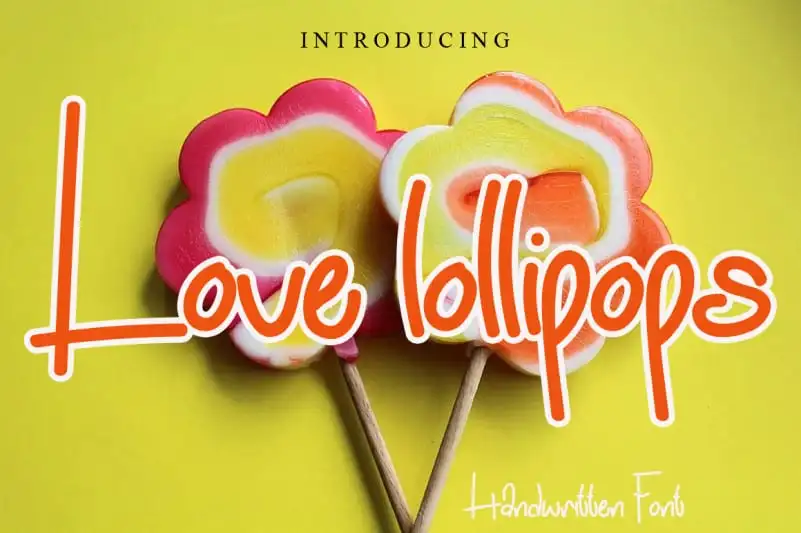
Love Lollipops Font – Fonte Grátis
Love Lollipops Font
A “Love Lollipops Font” é uma elegante escolha para quem quer adicionar um toque de delicadeza a seus designs digitais. Esta tipografia handwritten simples e fina captura a essência do saboroso gosto infantil, sendo ideal para criações variadas que vão desde logomarcas e materiais educacionais até cartões personalizados e ilustrações animadas. Com sua versatilidade impressionante, esta font pode ser empregada em uma vasta variedade de projetos. De um simples selo de felicidade no centro do seu site a uma coleção de letras coloridas para ensinar crianças sobre frutas, o “Love Lollipops Font” se adapta à perfeição, elevando seus designs para novos níveis de encantamento e simplicidade.